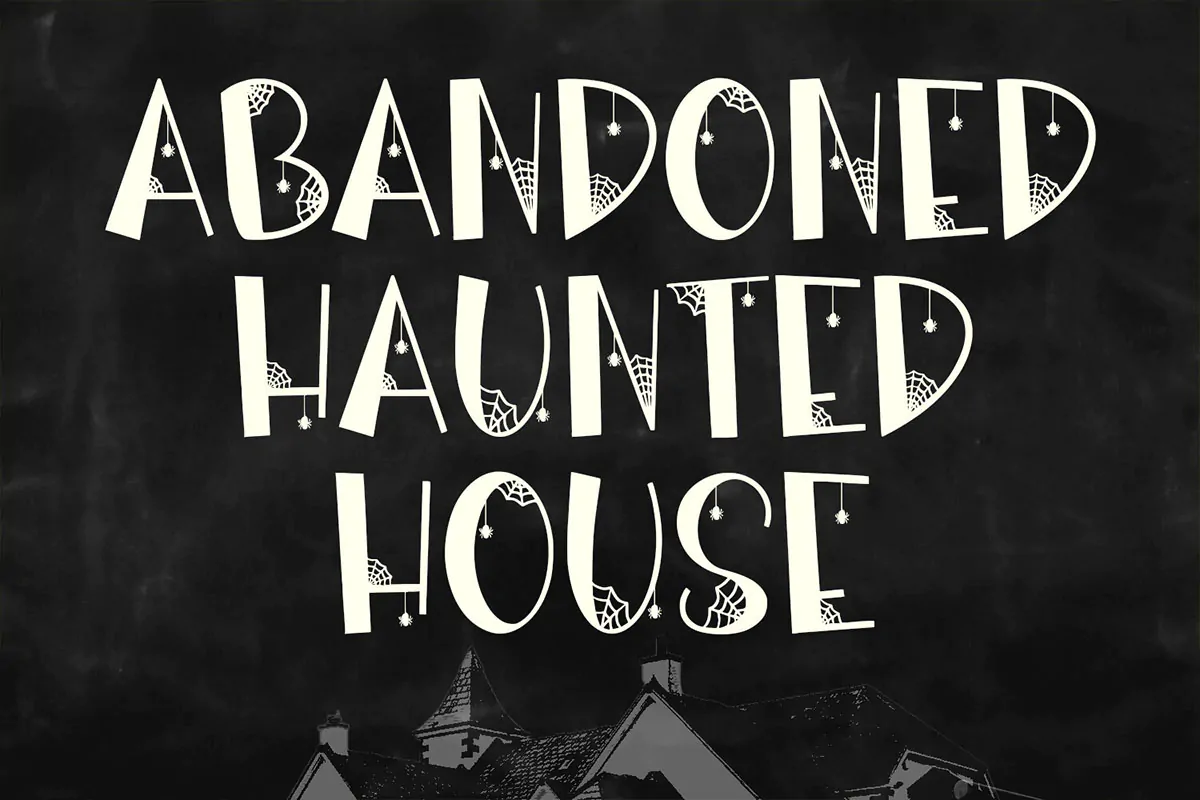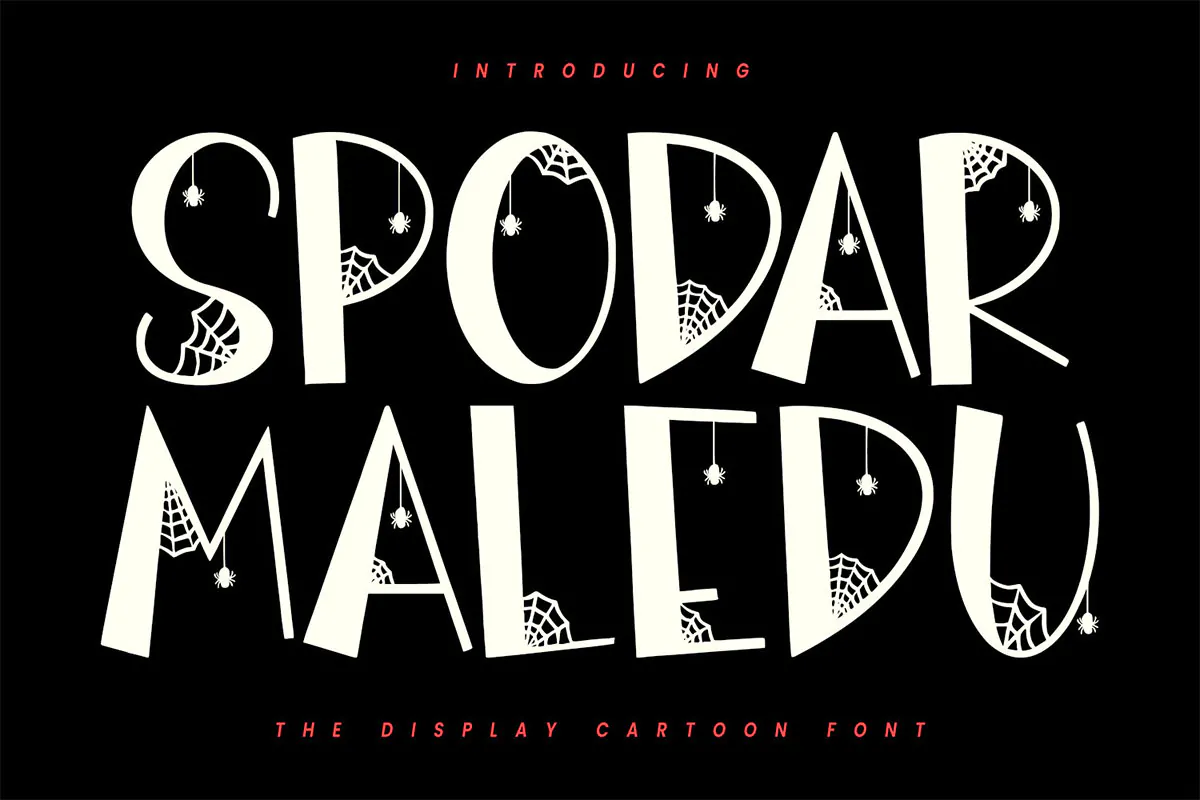
فونت کارتونی عنکبوتی و ترسناک Spodar Maledu
فونت کارتونی عنکبوتی و ترسناک
فونت کارتونی عنکبوتی و ترسناک Spodar Maledu یک قلم انگلیسی فوق العاده زیبا و جذاب نمایشی است که مناسب برای استفاده در طرح و پروژههای گرافیکی مختلف به خصوص طراحی پوسترهای هالووین میباشد.